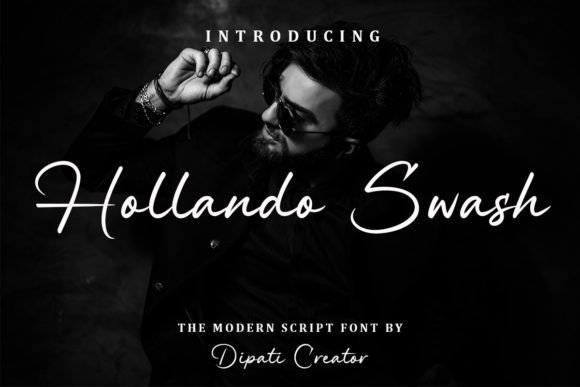
Hollando Swash
Wenn Sie nach hochwertigen Assets wie Hollando Swash suchen, ist dieses Premium-Paket eine fantastische Wahl für Ihre kreativen Projekte.
Egal, ob Sie POD-Produkte (Print on Demand), Hochzeitseinladungen oder Social-Media-Grafiken erstellen, Hollando Swash ist die ideale Wahl.